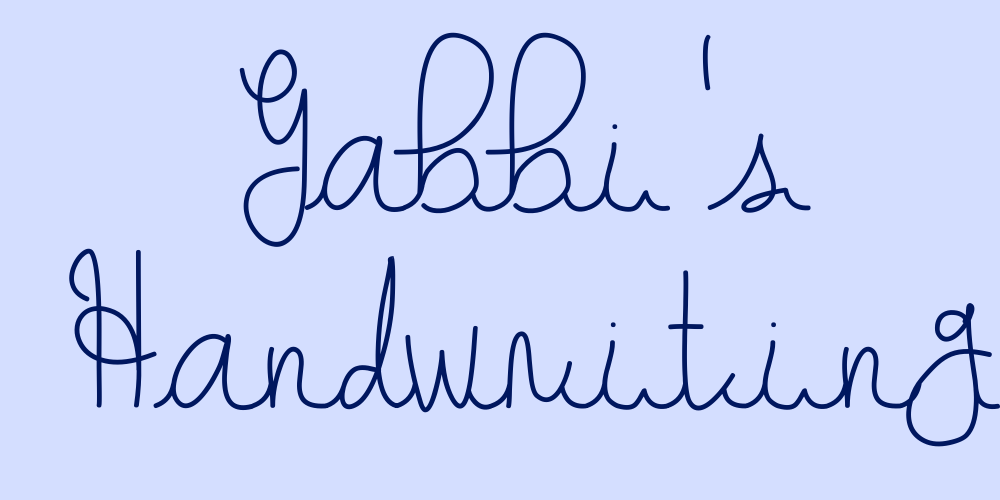
A fonte ‘Gabbi’s Handwriting’ é uma elegante escolha para designers que procuram transmitir um toque romântico ou sofisticado em suas criações digitais. Desenhada pelo designer Hamilton, essa fonte apresenta traços fluidos e bem trabalhados que trazem ao seu trabalho uma autenticidade única e envolvente. Seu estilo desenho natural remete à escrita a mão de um artesão excepcional, proporcionando um toque especial às letras. Esta fonte é perfeita para aplicar em design de blogs, gráficos publicitários ou até mesmo em projetos de ilustração. O resultado será uma mensagem que ressoará com o público alvo, encantando-os e deixando uma impressão duradoura. Experimente ‘Gabbi’s Handwriting’ para dar um toque único à sua próxima criação digital.